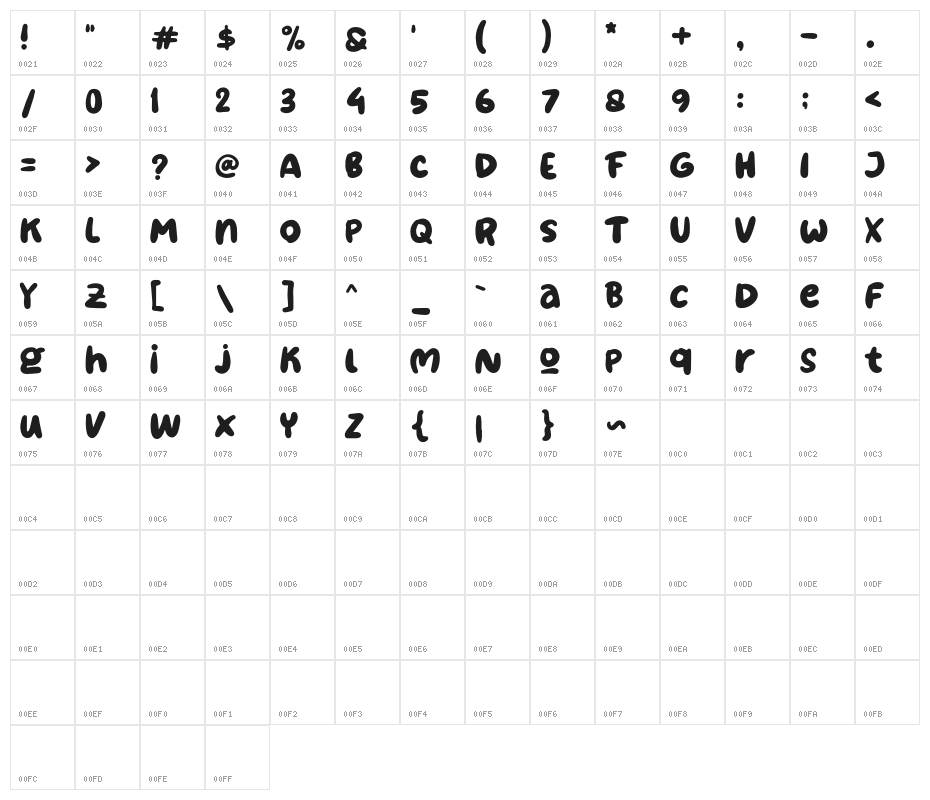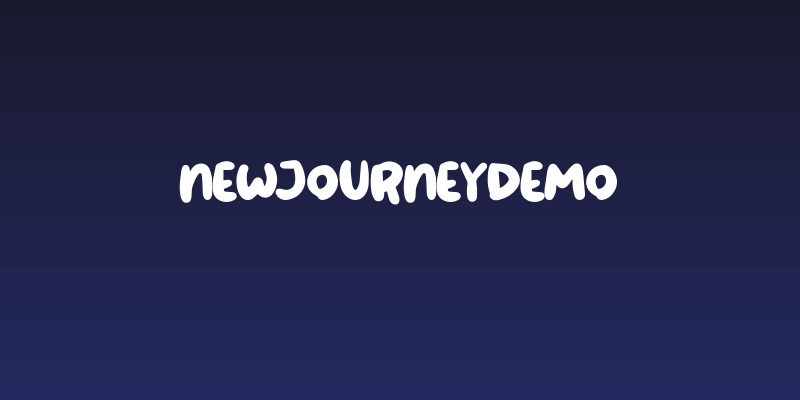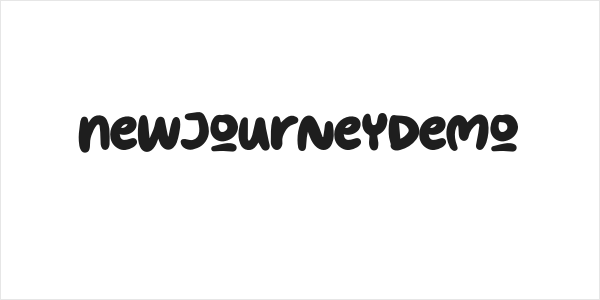
NewJourneyDemo Font
Cette police comprend 93 caractères. Cliquez sur un caractère pour voir les détails.
| Famille de police | New Journey Demo |
| Style général | Playful |
| Projets proposés | Ideal for children's books, playful branding, posters, and social media graphics. |